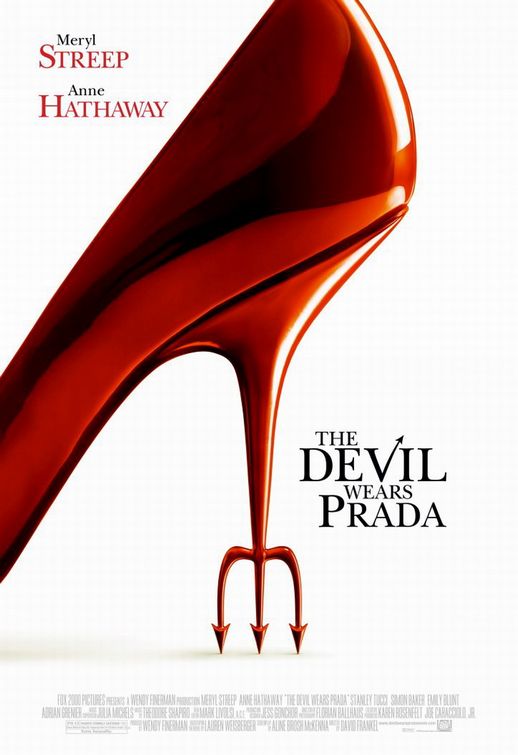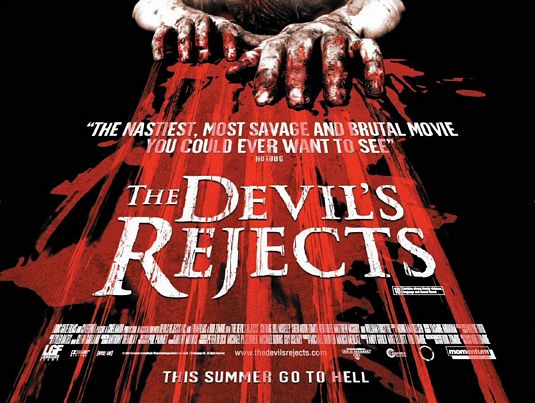
ok, spass beiseite. kommt immer drauf an was du unter 'teuflisch' verstehst.
es gibt keine teuflischen fonts, sondern es hängt auch immer von deiner restlichen gestaltung ab.
es sei denn, du suchst sowas wie die snowcaps nur mehr in richtung hölle, wobei mehr fast nicht möglich ist.
ein passender kanditat wäre eventuell:
A Theme for Murder
distorted, destroyed und trashig geht sicher auch.